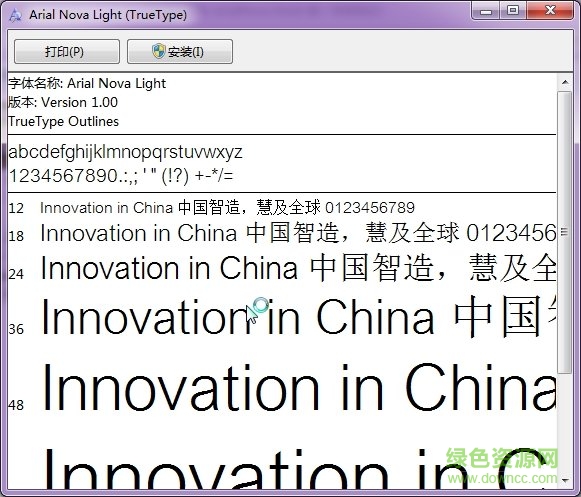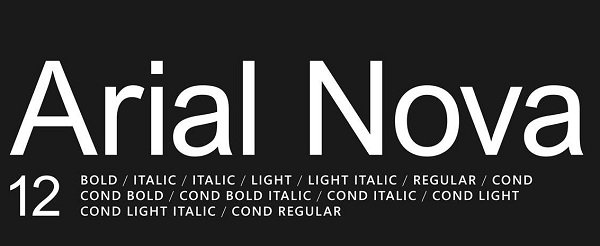
win10 Arial Nova字體
arial nova字體介紹
一款名為Arial Nova字體被發(fā)現(xiàn)出現(xiàn)在微軟商店中,這是一款經(jīng)典Arial家族經(jīng)過演變和重新設(shè)計(jì)的字體,適用于文件的段落和標(biāo)題。該字體下載需要使用最新的Windows 10預(yù)覽版系統(tǒng),并加入Insider計(jì)劃。
字體特色